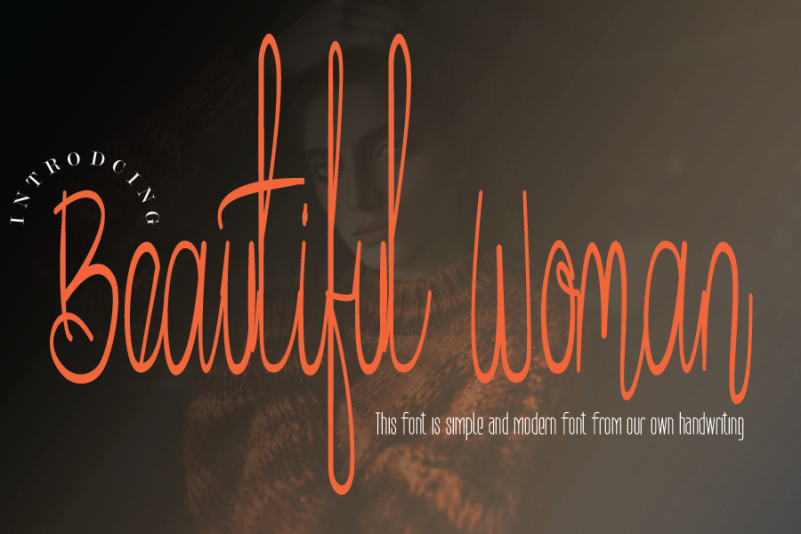
Beautiful Woman Font – Download Grátis
Esta fonte ‘Beautiful Woman Font’ é uma tipografia escrita a mão com equilíbrio perfeito e refinamento, transmitindo sofisticação e elegância. Suas alternativas estilizadas e ligaturas tornam esta fonte perfeita para qualquer projeto. Através de linhas delicadas e gestos suaves, essa fonte captura a essência feminina com uma certa graça. É perfeita para anúncios de moda, gráficos publicitários ou até mesmo para criar rascunhos emoticonos que expressam elegância feminina em um toque. Se você está buscando uma fonte de escrita a mão que exalasse sofisticação, a ‘Beautiful Woman Font’ é uma escolha perfeita.